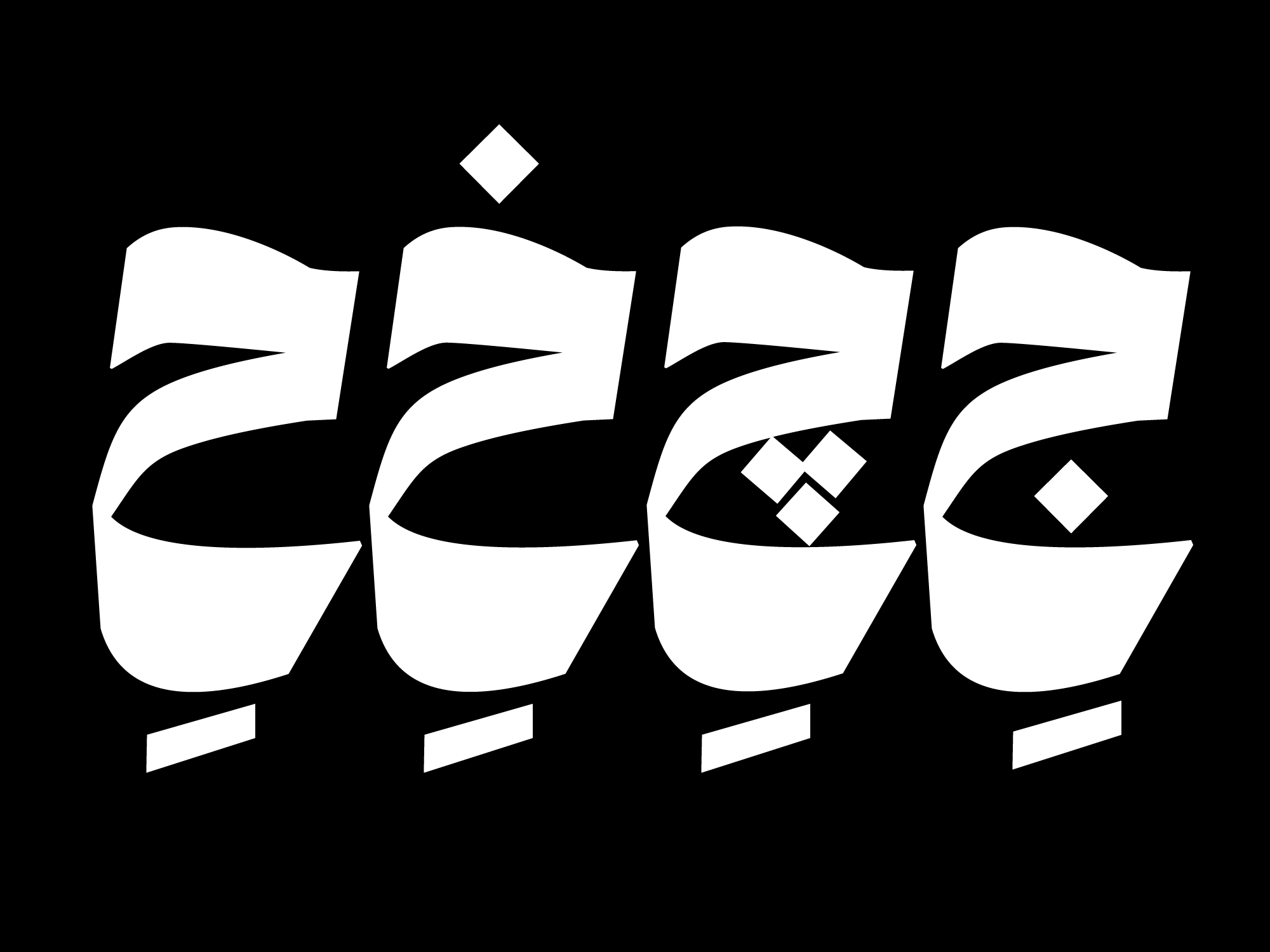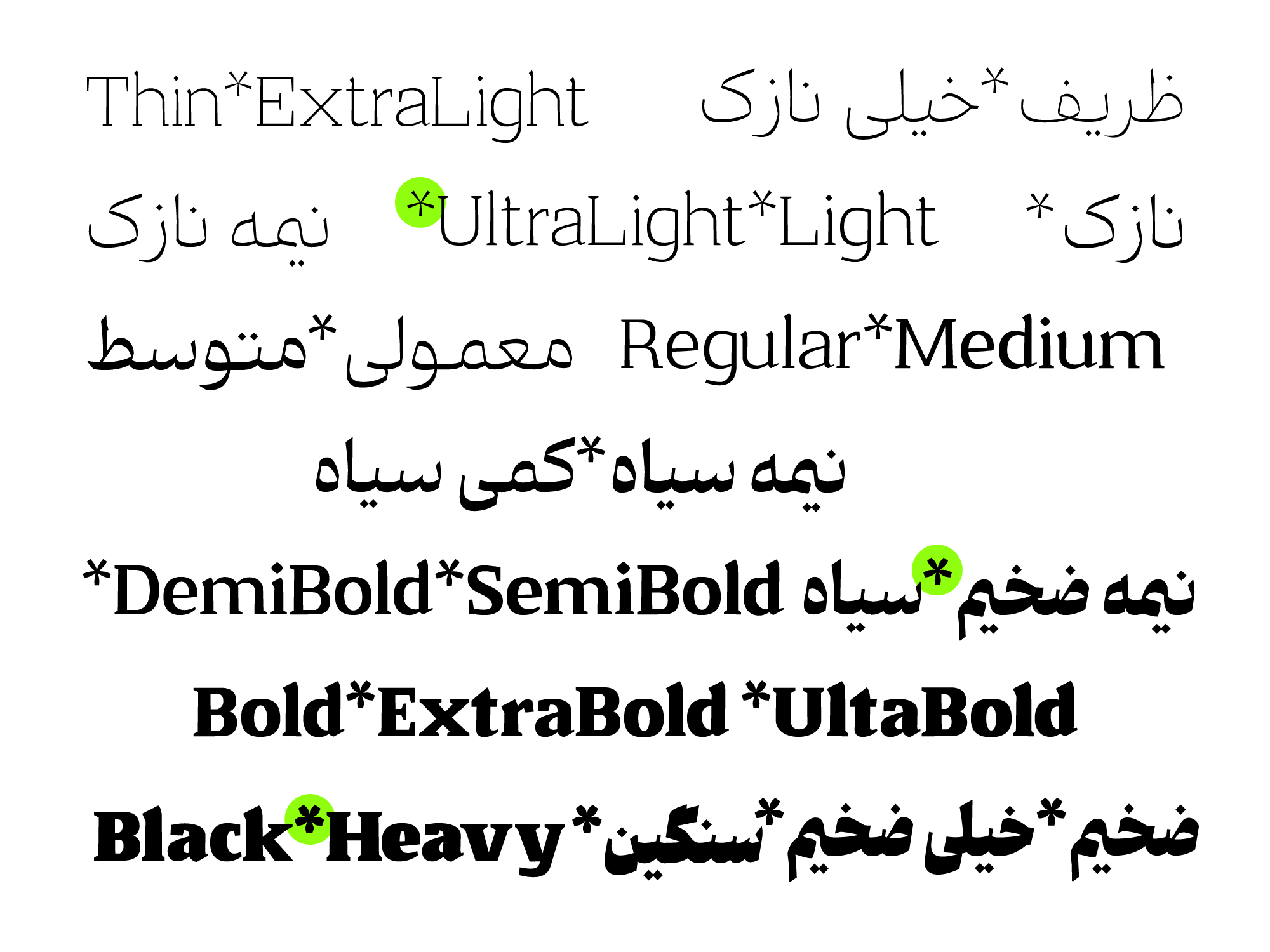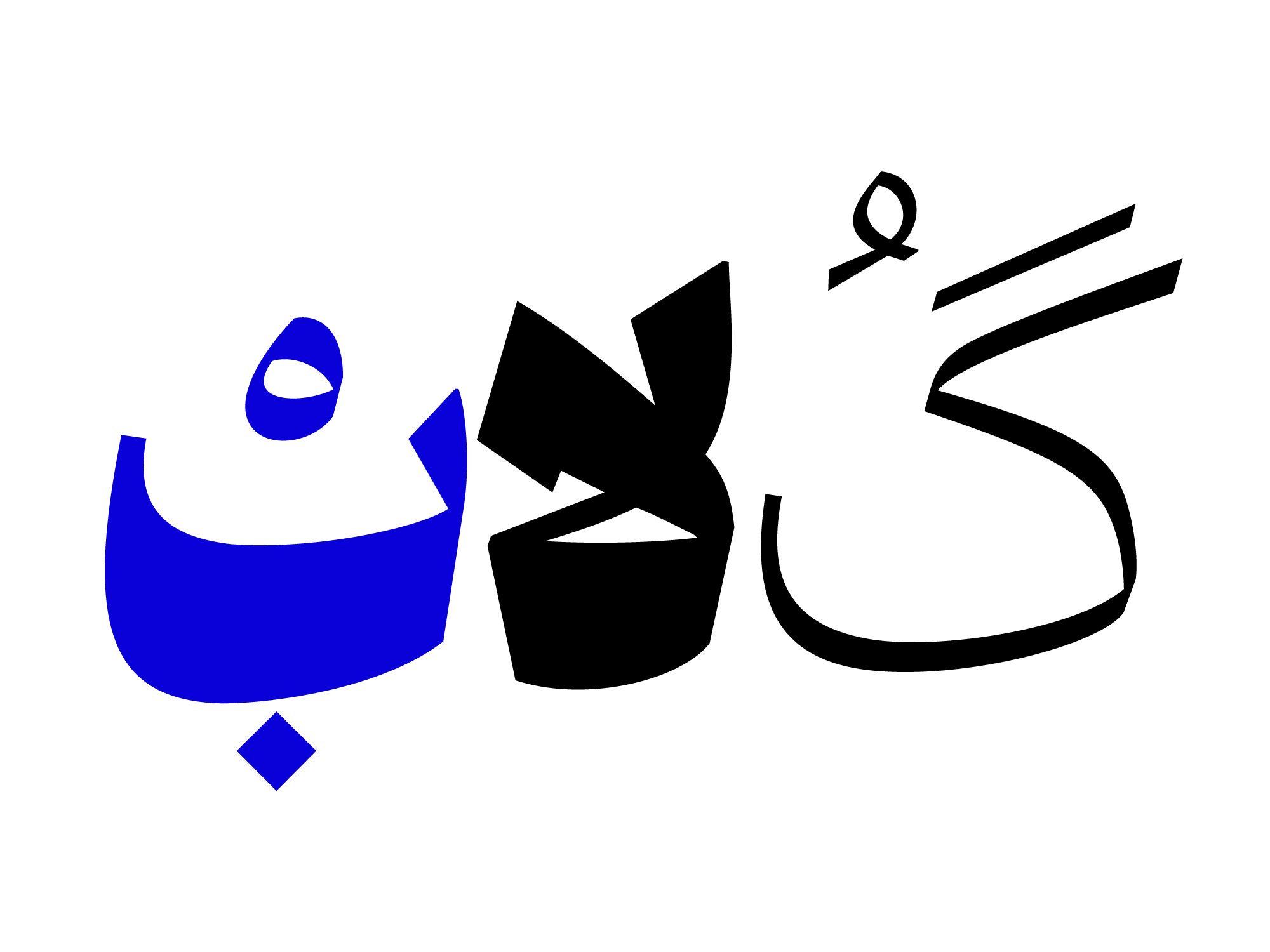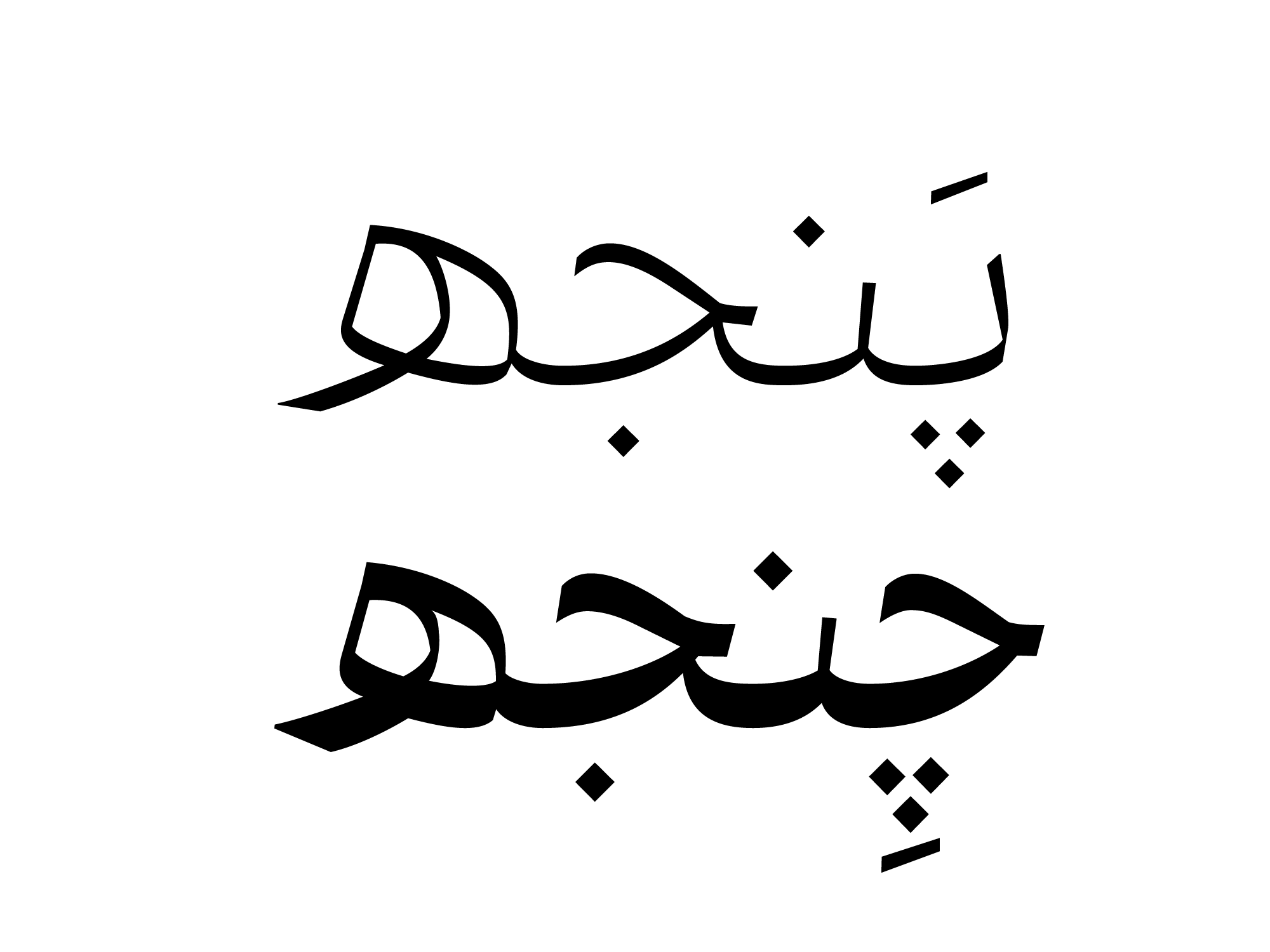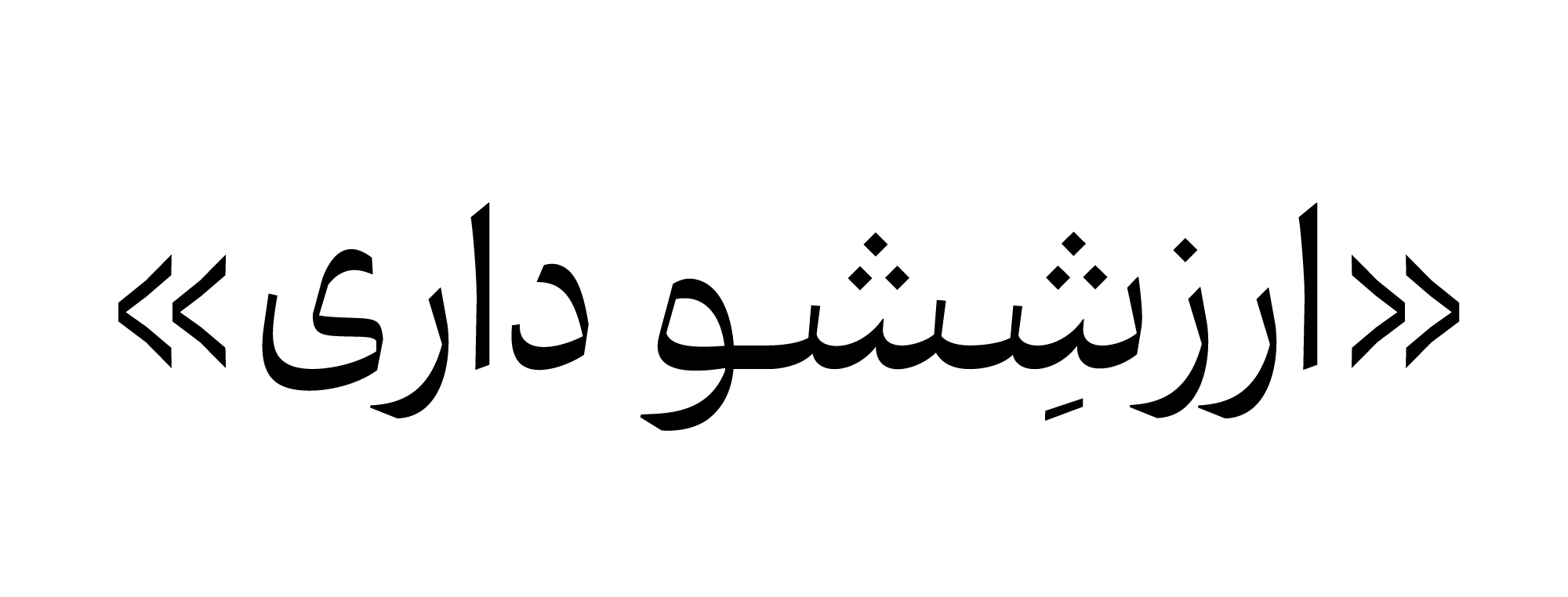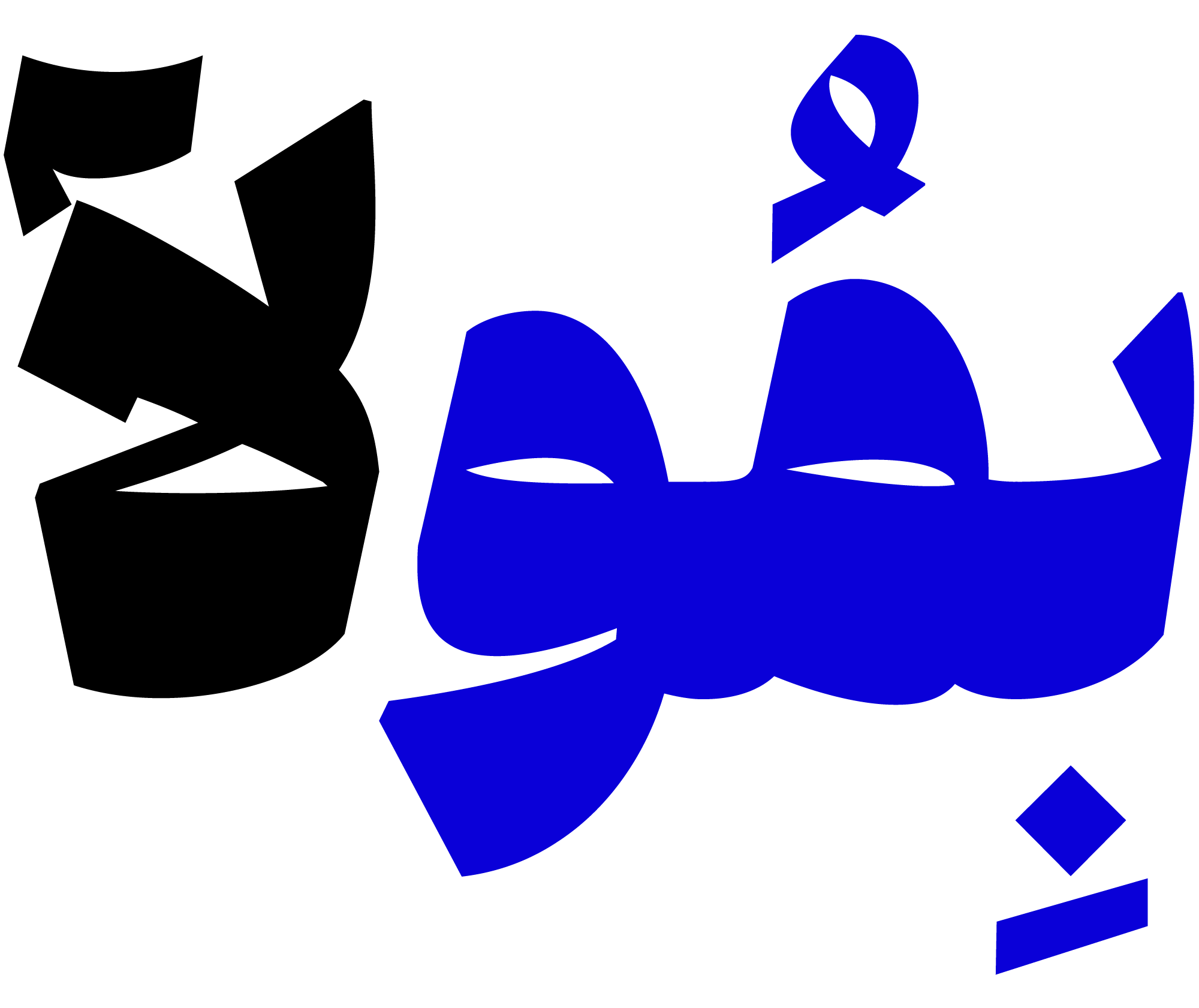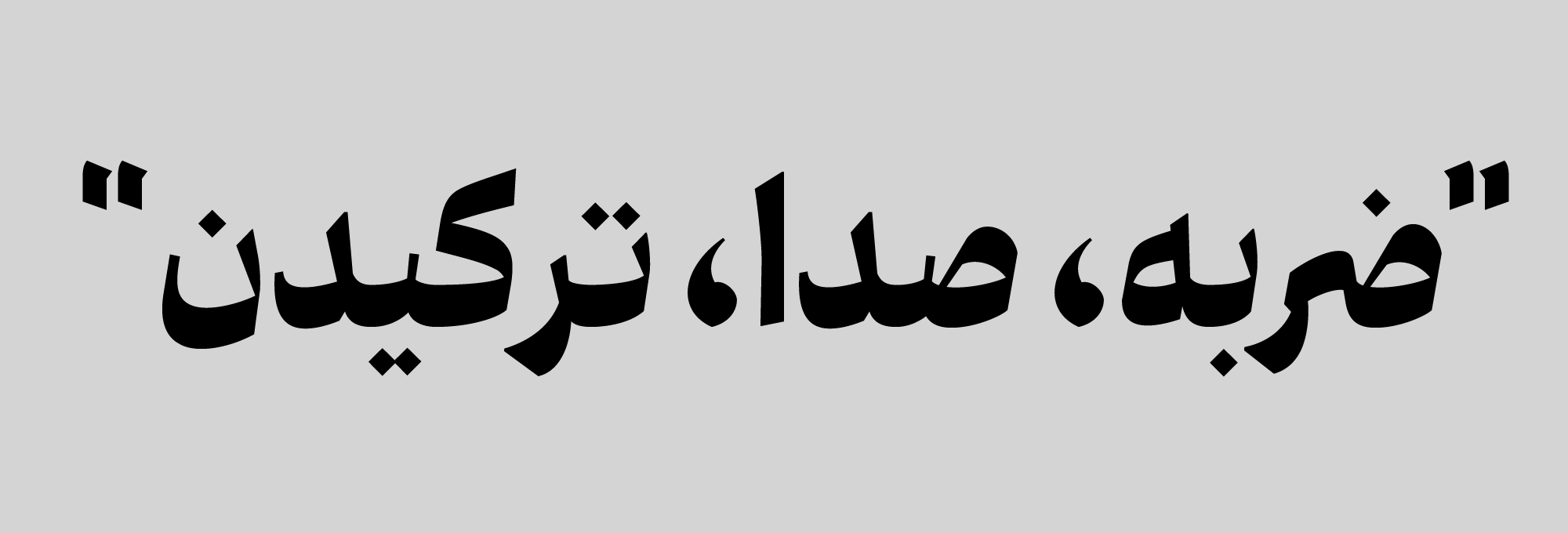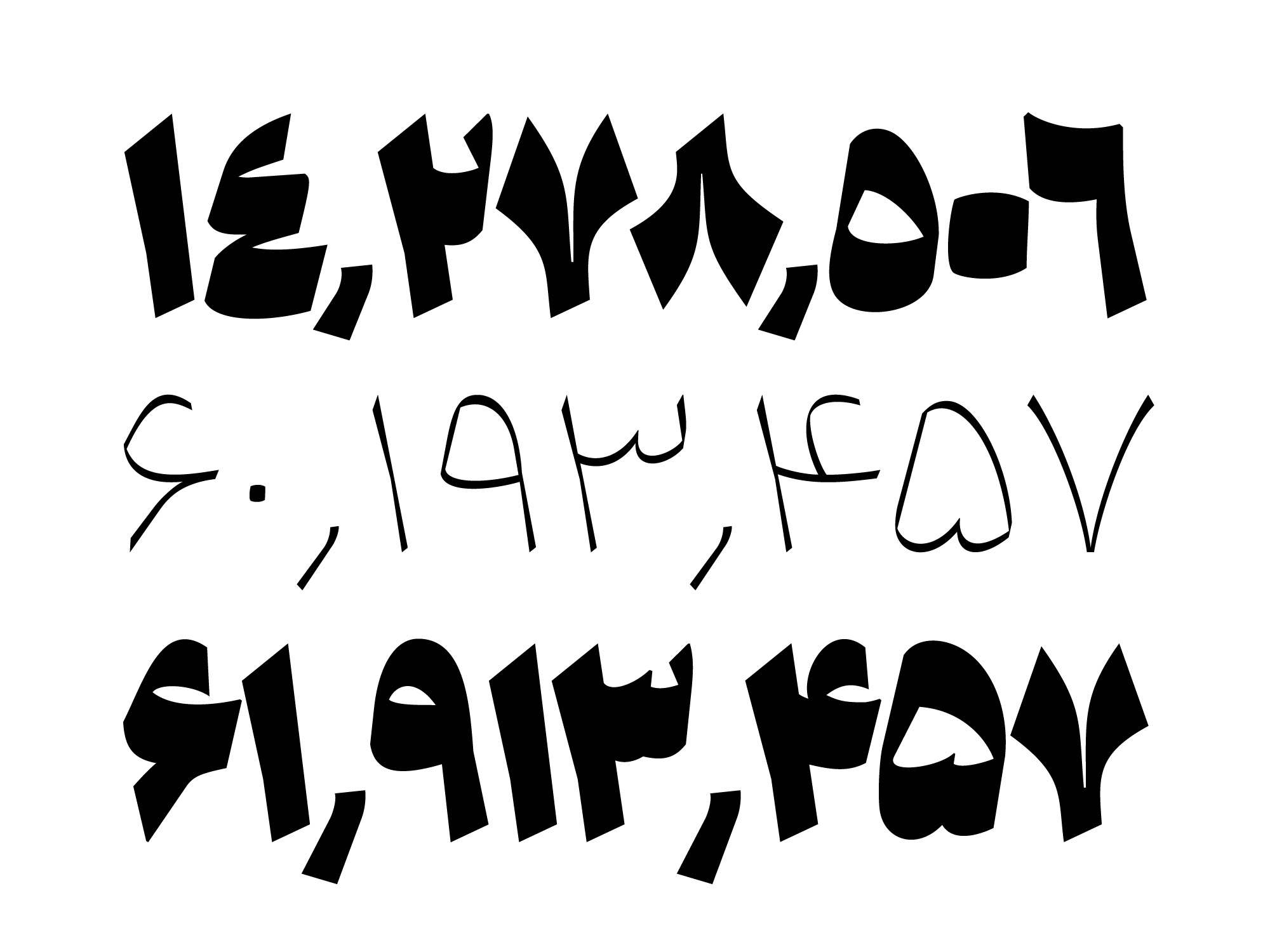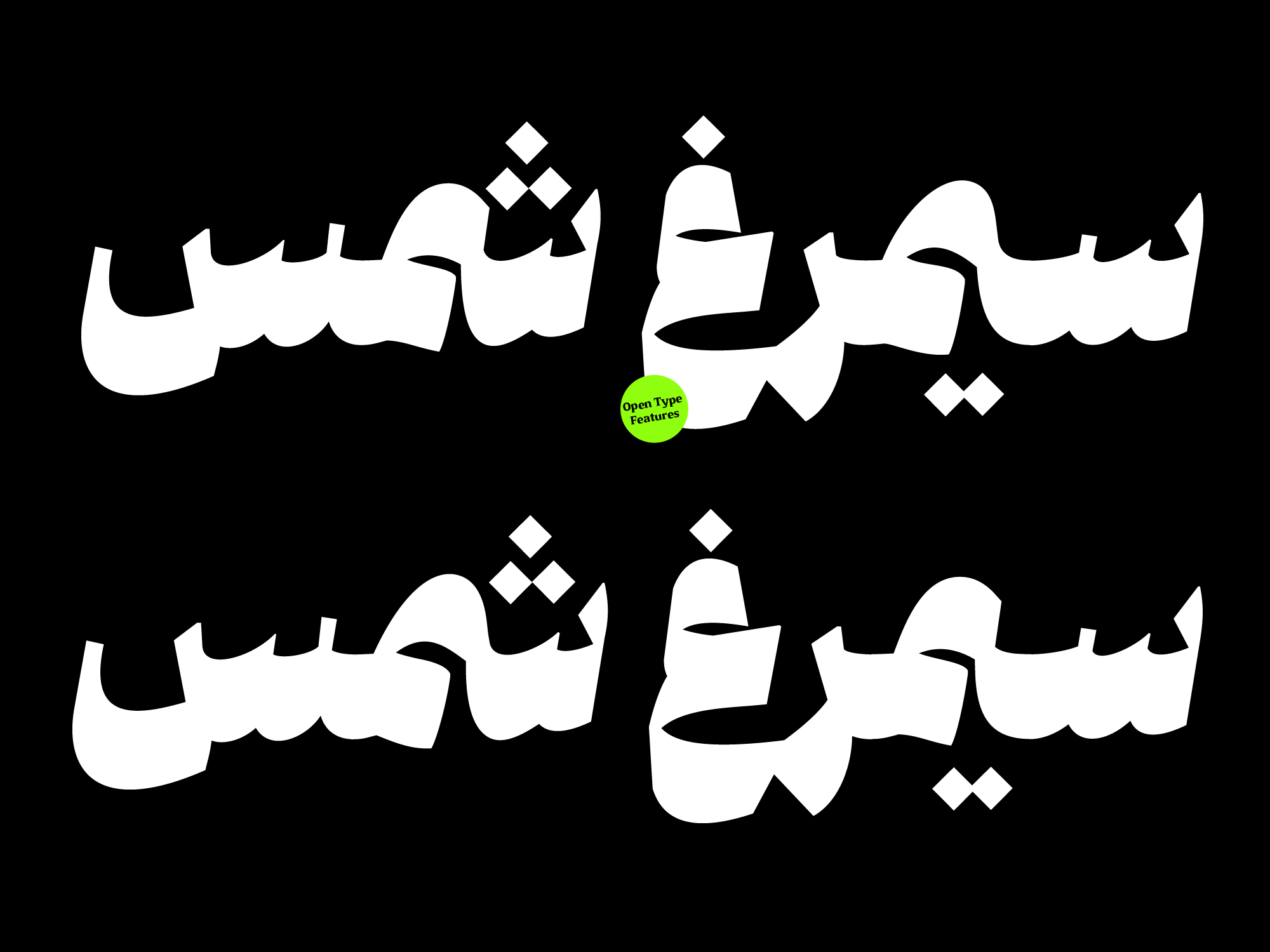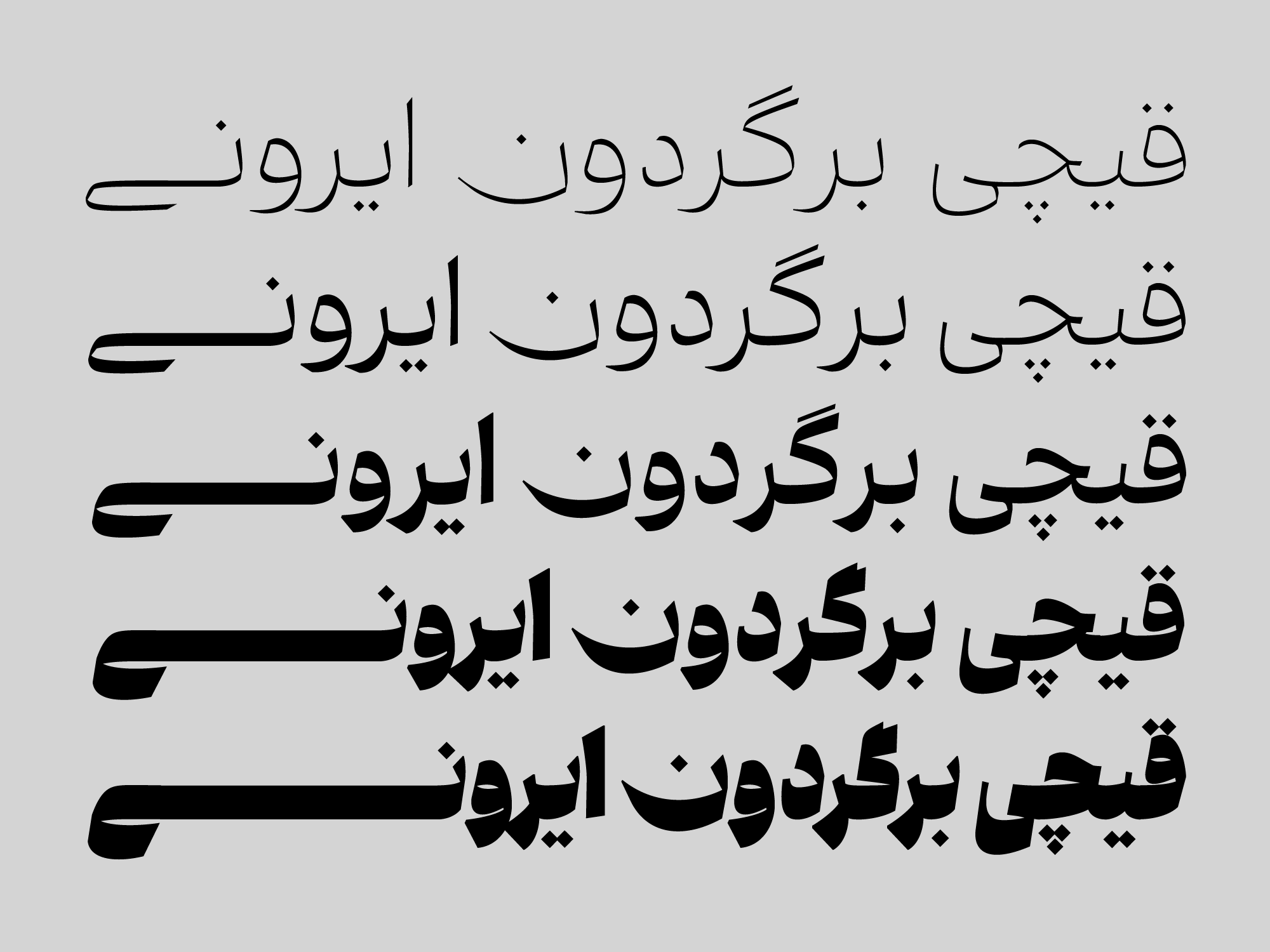
"ونوو" یک تایپفیس غیر رسمی است که میتواند توجهها را به خود جلب کند. در ابتدا، هدف اصلی از طراحی فونت ونوو ، تولید یک تایپفیس تنوعبخش در یک وزن سنگین بود. اما در طول فرآیند طراحی، با در نظر گرفتن قابلیتهای فرمی، به یک خانواده مدرن گسترش یافت تا بتواند نیازهای مختلف را برآورده کند.
یکی از ویژگیهای بارز فونت ونوو، تعامل بین ضخامت حروف است که به آن جذابیت و استحکامی مدرن میبخشد. این ویژگی بین فرمهای سخت و نرم، فونت ونوو را به یک تایپفیس منحصر بهفرد تبدیل کرده است. وزنهای ضخیم و سنگین این تایپفیس دارای کنتراست ضخامت بیشتری هستند که به تیترها و عنوانها زندگی میبخشند و دارای یک بافت متفاوت و برجسته است. خانواده فونت ونوو شامل سیزده وزن مختلف از ظریف تا سنگین است و با داشتن مجموعهای از کاراکترهای جایگزین، فضای تایپوگرافی جذابی را به ارمغان میآورد.
فونت ونوو از حروف و ترکیبات چند حالتی پشتیبانی میکند. این به این معنی است که فونت ونوو دارای حروف کشیده، جایگزین و حروف ترکیبی دو و سه کاراکتری است و با استفاده از این امکانات، میتوانید حروف را با حالتهای مختلف نمایش داده و نسخههای متفاوتی را انتخاب کنید. با استفاده از این حالتها و ویژگیها، شما میتوانید ظاهر و طرح متن و کلمات خود را در فونت ونوو متنوعتر و جذابتر کنید.
فونت ونوو از زبانهای کردی و عربی پشتیبانی میکند و به کاربران این زبانها اجازه میدهد تا از این تایپفیس در نوشتار و طراحیهای خود استفاده کنند. همچنین برای متنهای دوزبانه (چندخطی)، خانواده حروف لاتین آن نیز طراحی شده است تا تعامل بین این دو نوع حروف به بهترین شکل حفظ شود و هماهنگی با کیفیتتری را به نمایش بگذارد.
تعامل در ضخامت حروف یکی از جنبههای بارز و مهم یک تایپفیس است که به آن جذابیت و استحکام میبخشد. و از طرف دیگری، فرمهای سخت و نرم به یک تایپفیس ظاهری منحصربهفرد و متنوعی ايجاد میکند. نتیجه تعادل و تناسب فرمهای سخت و نرم با ضخامت حروف، یک تایپفیسی خواهد بود که دارای جذابیت و ظاهری مدرن و قوی است. تماشای این تعامل بین ضخامت حروف در "ونوو"، نه تنها انسجام و هماهنگی میدهد، بلکه به طراحان گرافیک و تایپوگرافرها نیز این امکان را میدهد تا با استفاده از این تنوع و تعامل، طرحهای خلاقانه و جذابی را با توجه به دیدگاه و سبکشان دیزاین کنند.